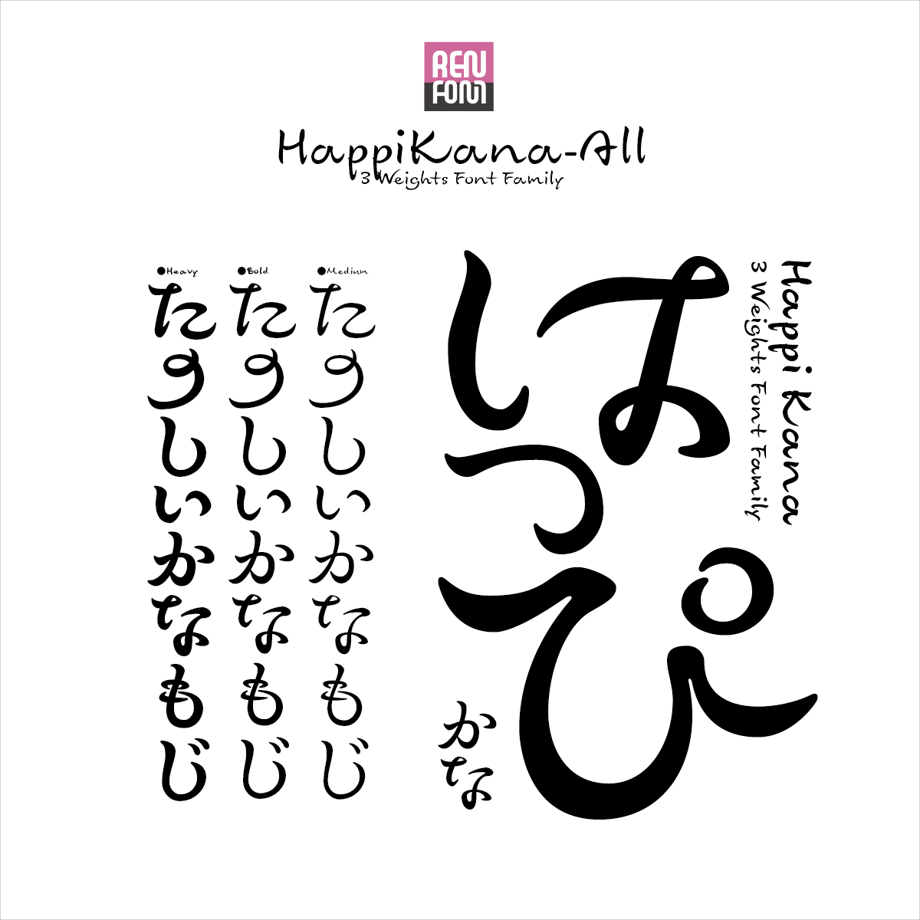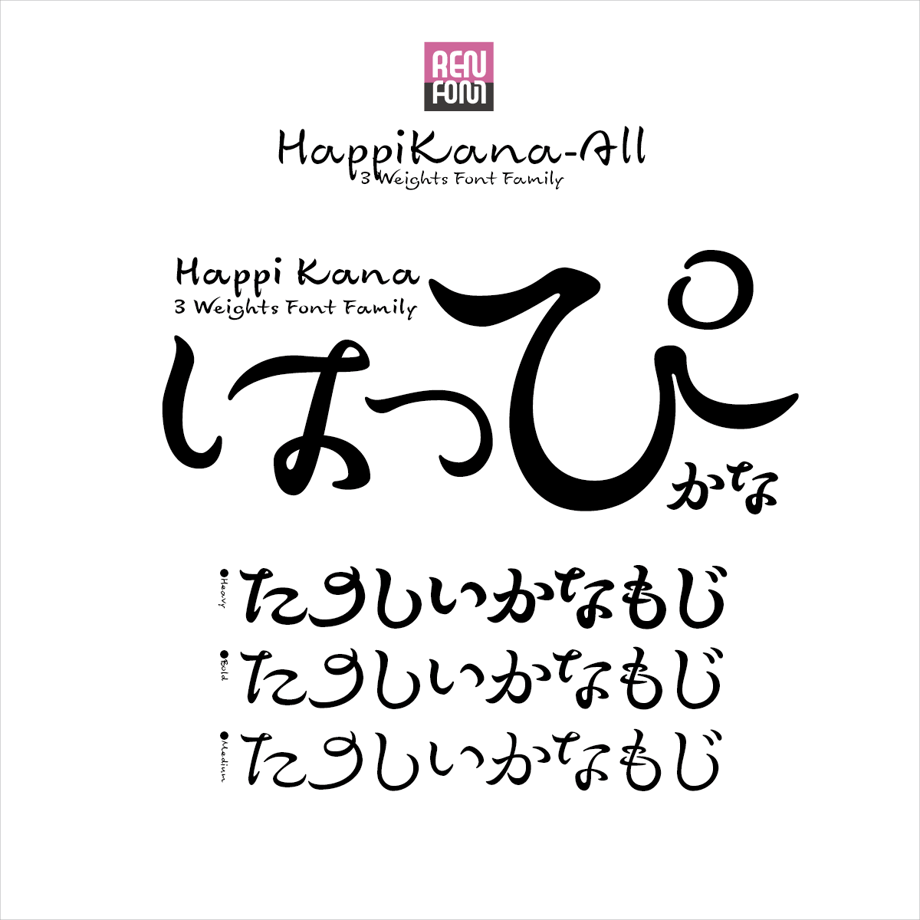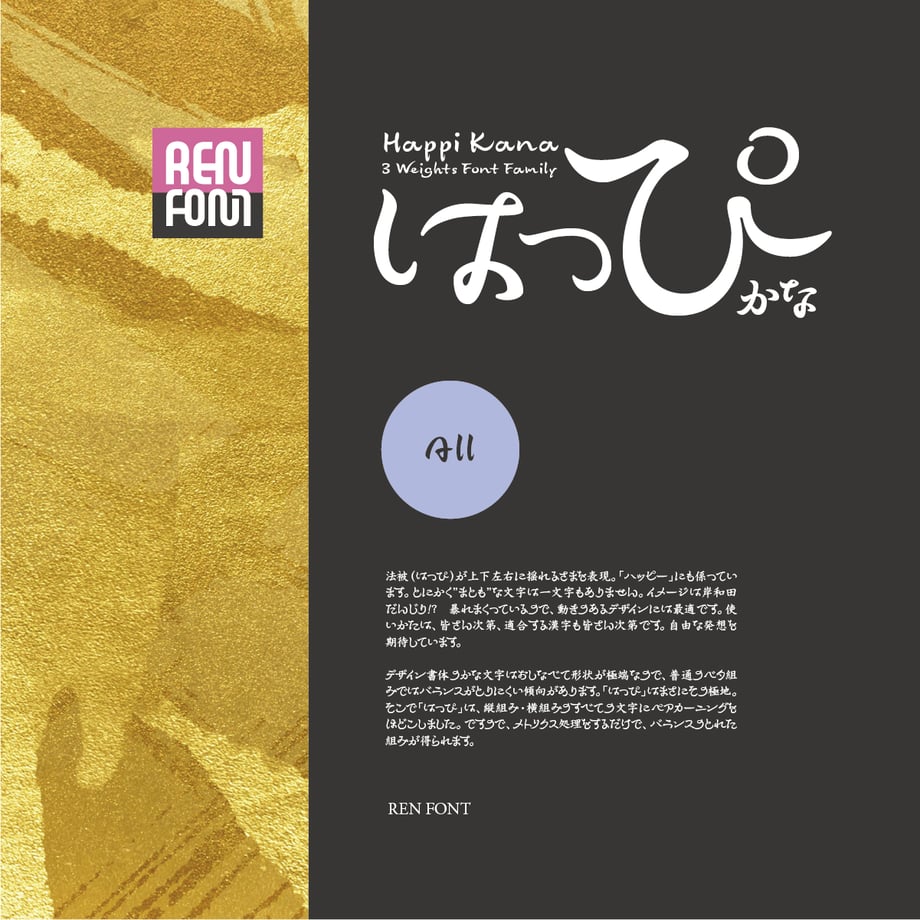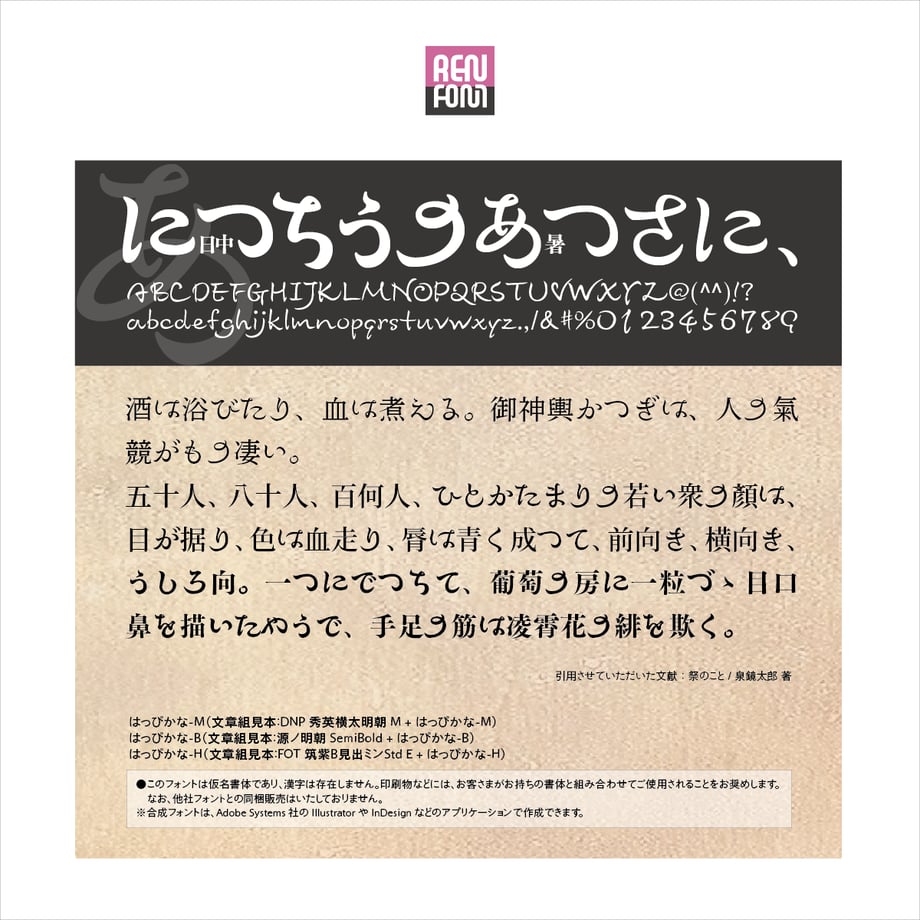
はっぴかな-All
祭りの楽しさがモチーフ
明朝体とかすかに隷書の名残り、楽しさ溢れる愉快な文字。
法被(はっぴ)が上下左右に揺れるさまを表現。「ハッピー」にも係っています。とにかく”まとも”な文字は一文字もありません。イメージは岸和田だんじり!? 暴れまくっているので、動きのあるデザインには最適です。使いかたは、皆さん次第、適合する漢字も皆さん次第です。自由な発想を期待しています。
デザイン書体のかな文字はおしなべて形状が極端なので、普通のベタ組みではバランスがとりにくい傾向があります。「はっぴ」はまさにその極地。
そこで「はっぴ」は、縦組み・横組みのすべての文字にペアカーニングをほどこしました。ですので、メトリクス処理をするだけで、バランスのとれた組みが得られます。
お祭り騒ぎを文字にすると…。
この書体は、当社タイプデザイナー金井和夫の普段使いの文字をベースとしてデザインされたものです。明朝体とわずかに隷書の痕跡を残した、暴れまくるデフォルメイメージを持っています。「M(ミディアム)」から「H(ヘビー)」までの、3ウェイトで構成されています。
個性があまりにも強いので、文章には向きませんが、ちょっとした見出しなどに使ってみてください。躍動感に満ちた、訴求力のある紙面になるはずです。縦組み、横組みともプロポーショナル加工を加えました。また、ペアカーニングもほどこしてあります。
他社「総合書体」との「共存」
この書体は、当社タイプデザイナー金井和夫の普段使いの文字をベースとしてデザインされたものです。明朝体とかすかに隷書の名残りを含んだ、楽しさ溢れる愉快な文字です。
個性があまりにも強いので、文章には向きませんが、ちょっとした見出しなどに使ってみてください。躍動感に満ちた、訴求力のある紙面になるはずです。縦組み、横組みともプロポーショナル加工を加えました。また、ペアカーニングもほどこしてあります。
合成フォントに向く漢字は限られてきますが、明朝だけではなく、楷書、教科書体、行書、また、ゴシックと組み合わせても面白い効果が期待できます。アイデア次第でどうにでもなる書体です。
基本的な形状は明朝体。若干の隷書も入りつつ…。とにかく暴れまくっているので、普通に組んでも動いているように見えます。特にカタカナは言ってみれば「はちゃめちゃ」です。動的なデザインにお使いいただくのがベストですが、案外童話などにも向くかもしれません。ただし、クライアントに叱られないよう、許可を取ってくださいね。
本来日本語フォントは正方形に納めるのがセオリーですが、「はっぴ」はそれを無視しています。したがって、ベタ組みでは、となりの文字と重なってしまう事態も起こります。細かいペアカーニングがほどこしてあるので、メトリクスでご使用されることをおすすめします。
両かなにイメージを合わせた、いわゆるブラッシュスクリプトです。思い切ってデフォルメした文字も随所に入っています。破天荒でバラエティに富んだ、リズム感あふれる書体になっています。使っているだけでウキウキしてくる、無条件で楽しい書体です。